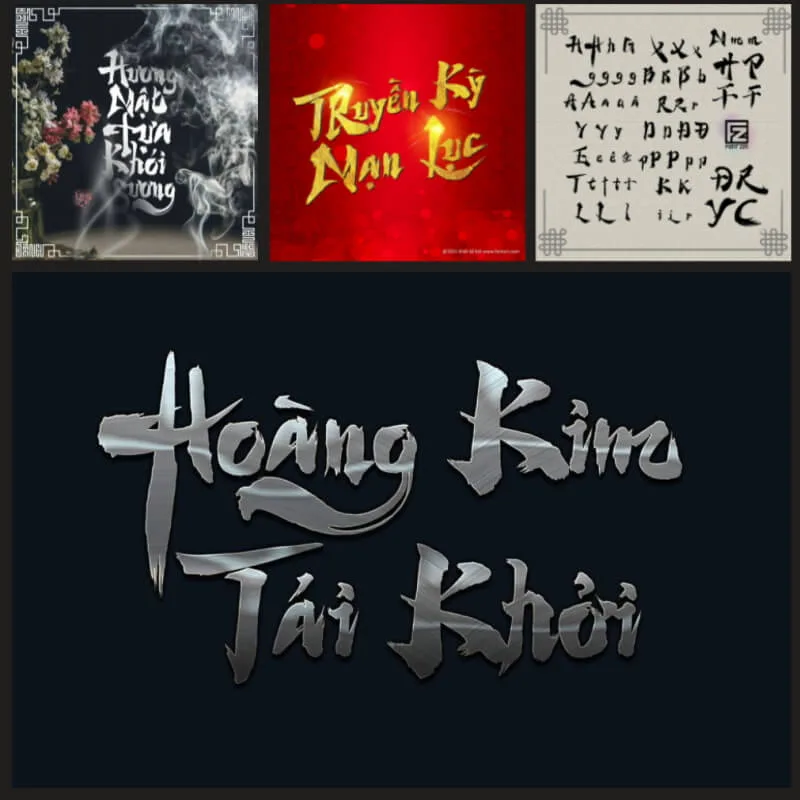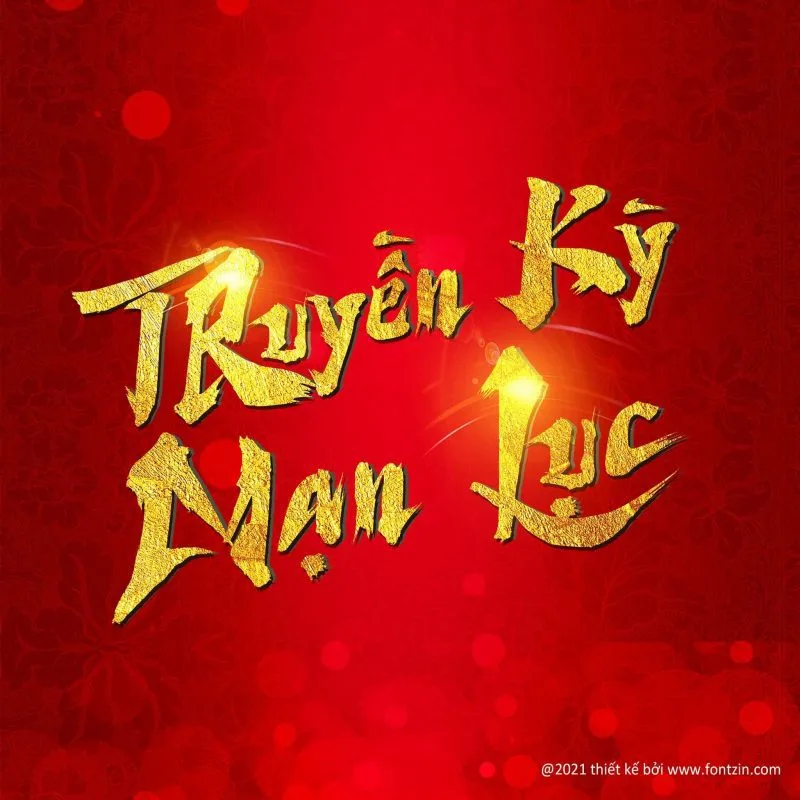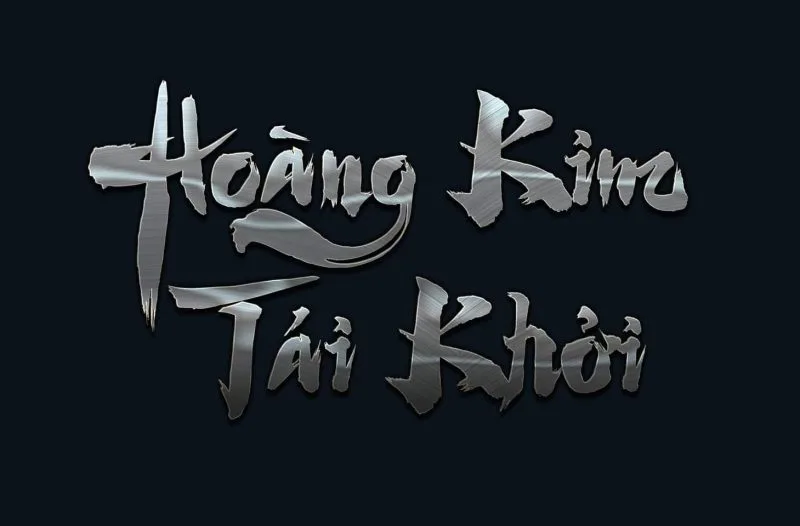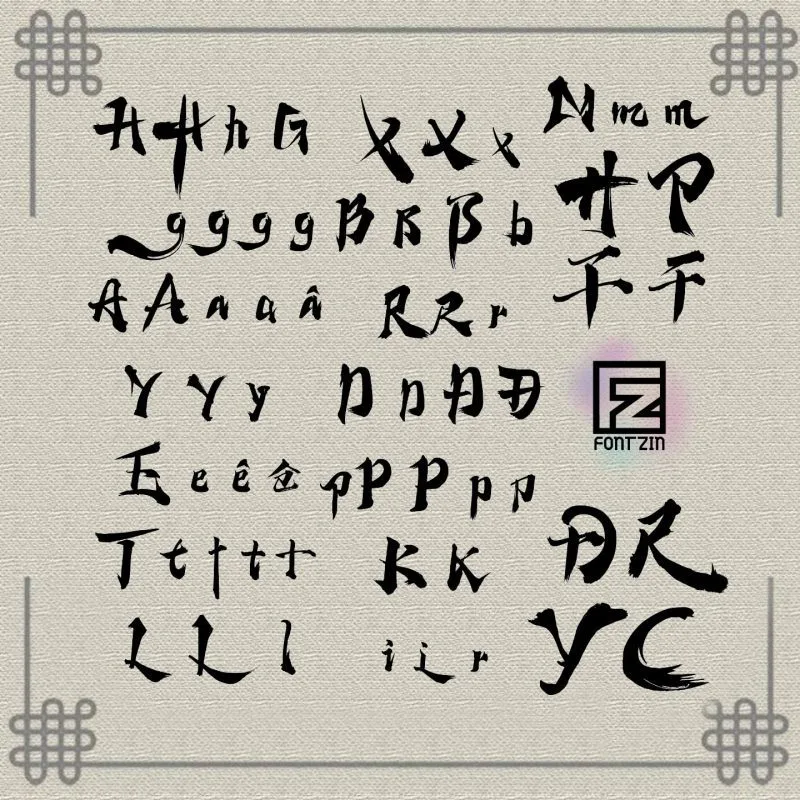
Font Fz Thư Pháp V2
Font Fz Thư pháp nằm trong seri font dành cho game kiếm hiệp. Font là sự kết hợp nét cọ cứng và phong cách hiện đại, lối viết phóng khoáng.
Bộ Font game kiếm hiệp Fz Thư pháp
Font là sự kết hợp của nét cọ cứng và phong cách hiện đại tạo nên sự phóng khoáng và đậm chất kiếm hiệp của bộ font này.
Giới thiệu Font Fz Thư Pháp
Font Fz Thư pháp nằm trong seri font dành cho game kiếm hiệp, phông chữ này được rất nhiều nhà phát hành game ở Việt Nam và Trung Quốc sử dụng. Font được thiết kế bởi admin Đức Thủy
Font Fz Thư pháp
Mục tiêu hướng tới của bộ font thư pháp fz là
Bộ font thiết kế ra nhằm mục đích thư nhất là góp phần làm phong phú nguồn font tiếng Việt. Thứ 2 là giúp cho các ấn phẩm về game mang cốt truyện kiếm hiệp và các ấn phẩm võ hiệp khác có phong cách thiết kế mới mẻ hơn.
Đặc tính của Font Fz thư pháp
Font thư pháp game fzthuphap
#1 Font được thiết kế dựa trên cảm hứng nét cọ của chữ hán.
#2 Font phù hợp design cho các sản phẩm về game và các ấn phẩm mang phong cách võ hiệp.
#3 Font có nhiều ký tự thay thế nhằm tạo sự linh hoạt trong việc thiết kế nội dung của sản phẩm
#4 Font được kerning và Việt hóa theo Unicode đầy đủ.